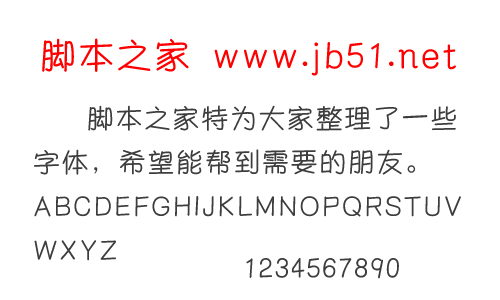
騰祥愛(ài)情體簡(jiǎn)繁字體是一款筆畫(huà)輕松、結(jié)構(gòu)疏緩的字體,使文字表達(dá)更加貼心與無(wú)微不至,該字體是由設(shè)計(jì)師孔淼手繪完成每個(gè)字形的原稿,再由騰祥公司調(diào)整修改完成的美術(shù)體字庫(kù),非常漂亮且舒服。一共有兩款粗細(xì),本款為愛(ài)情體。當(dāng)春三月,微風(fēng)輕拂,綿綿細(xì)雨,柳條輕搖,在這萬(wàn)物復(fù)蘇的季節(jié)“騰祥愛(ài)情體”生長(zhǎng)了。本款字閱讀流暢、筆畫(huà)舒展富于朝氣與生機(jī)。“心情就像風(fēng)一樣自由,愛(ài)情就在不遠(yuǎn)處等著你”在這浪漫的季節(jié)期待您與“騰祥愛(ài)情體”的美好邂逅噢!歡迎喜歡騰祥愛(ài)情體的朋友前來(lái)下載使用。